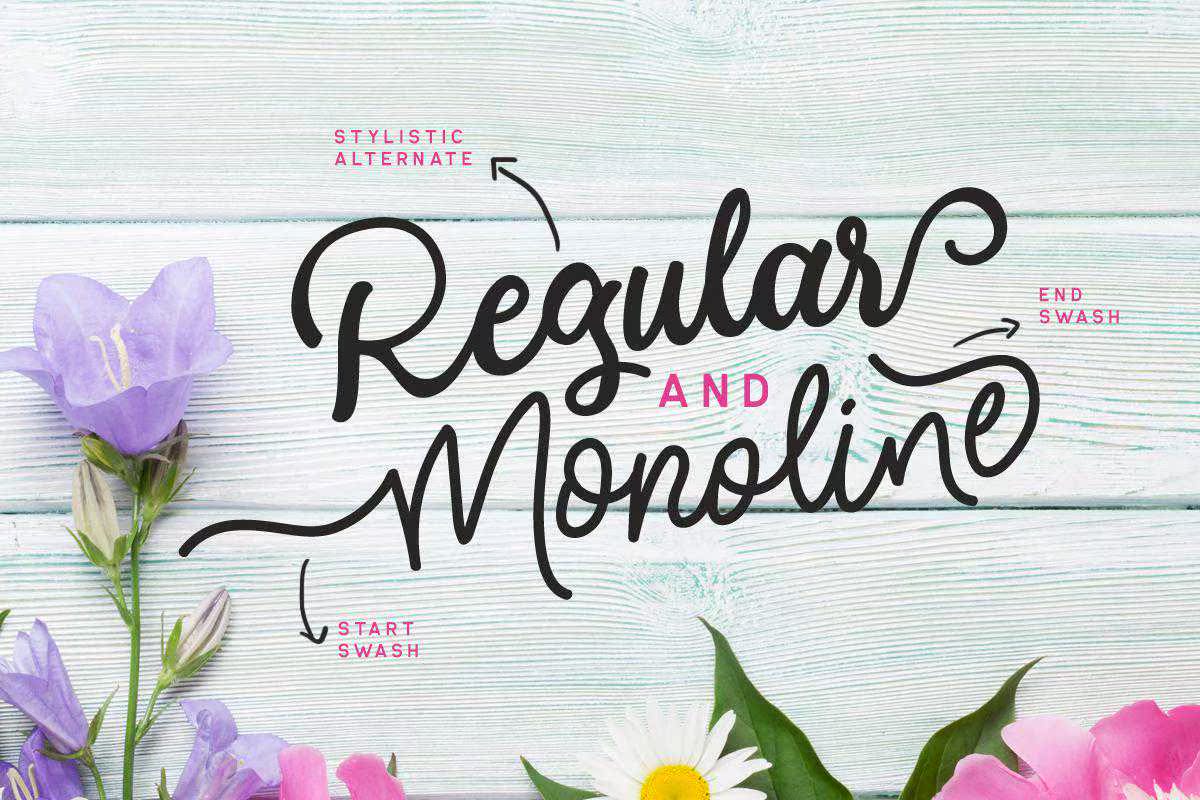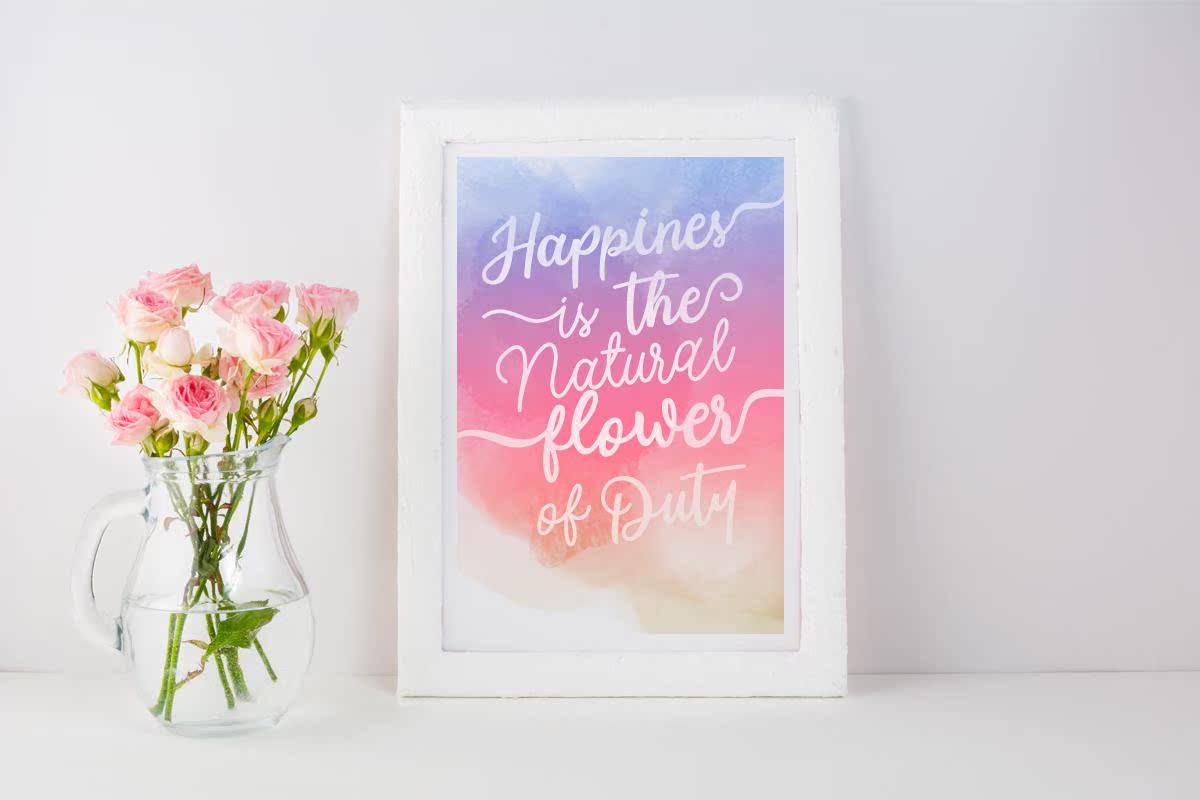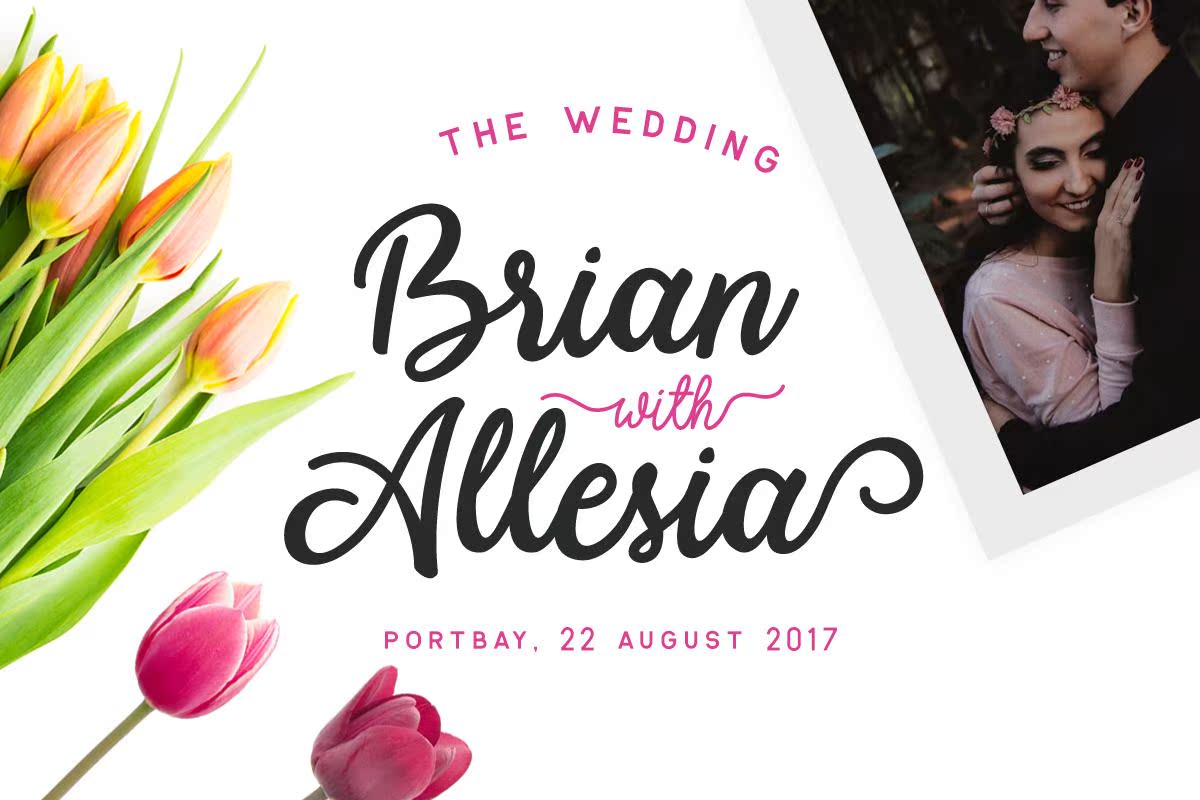
一个剧本!阿洛维利·丰杜奥斯特!这款Font有两种风格,一种是单色的,另一种是规则色的。非常适合女性化和少女化主题的项目!您可以使用Ligatures、StyleAlternate、swash等创建您自己的自定义字体。此字体还支持多语言。Modesta脚本!阿洛维利·丰杜奥斯特!这款Font有两种风格,一种是单色的,另一种是规则色的。非常适合女性化和少女化主题的项目!您可以使用Ligature、StyleAlternate、swash等创建自己的自定义文字。此字体还支持多种语言。